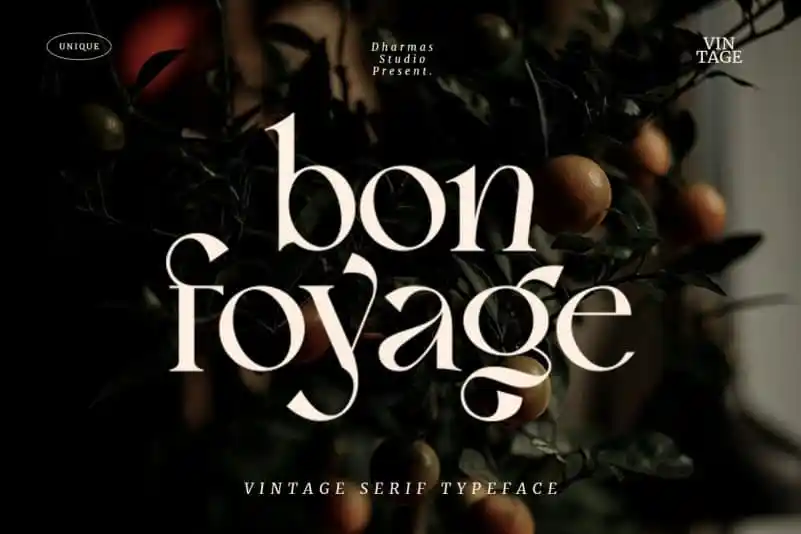
Bon Foyage Serif Font – Download Grátis
Bon Foyage Serif é uma fonte serif minimalista criada pela Dharmas Studio com um toque moderno, que traz elementos únicos em cada letra. Este design foi pensado para se destacar sem perder a elegância característica das fontes serif, ideal para os projetos que buscam equilíbrio entre o clássico e o contemporâneo. Uma das características mais marcantes da Bon Foyage é seu uso de ligaturas e alternativas de letras, que proporcionam um toque personalizado em cada letra. Isso permite criar designs com uma vibe vintage, sem perder a qualidade e os detalhes únicos presentes na fonte. Os alternativos para letras como ‘g’, ‘j’ e ‘y’ são particularmente memoráveis e permitem diferentes interpretações das mesmas figuras de texto. Ideal para designers que valorizam um equilíbrio entre o moderno e o vintage, Bon Foyage é uma excelente opção para aqueles que buscam uma fonte serif que ofereça tanto estilo quanto personalidade. Com seus elementos únicos em cada letra, este design se destaca não apenas por seu aspecto elegante, mas também pela sua capacidade de criar um ar de modernidade e atemporal ao mesmo tempo.